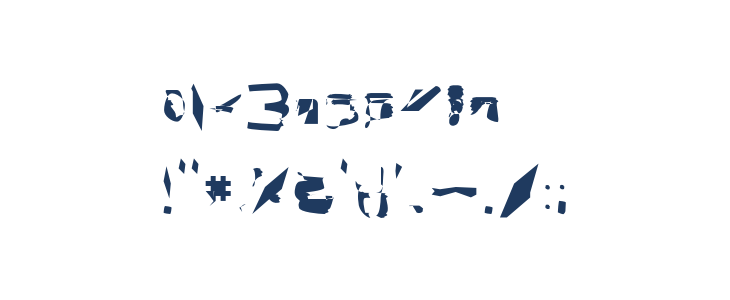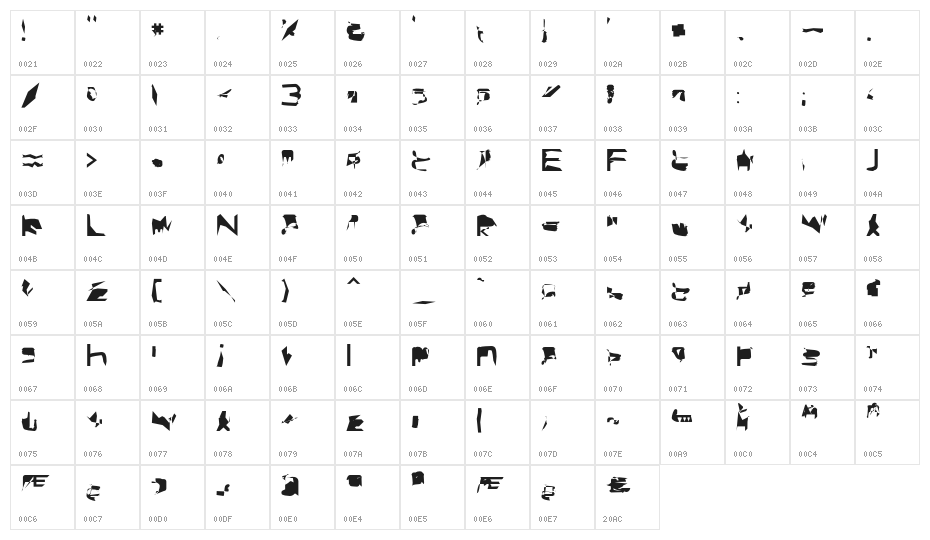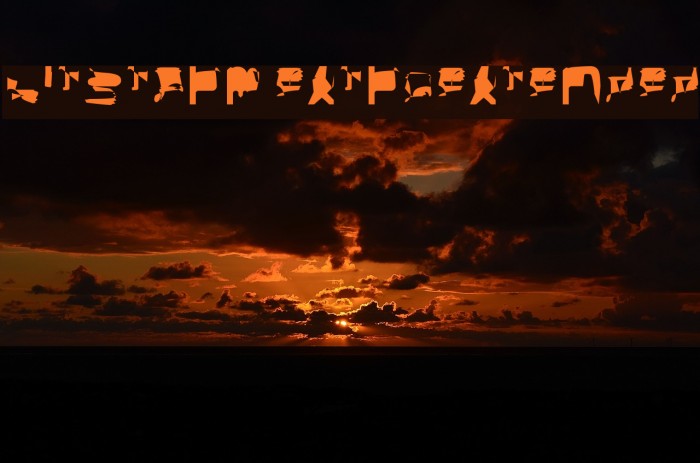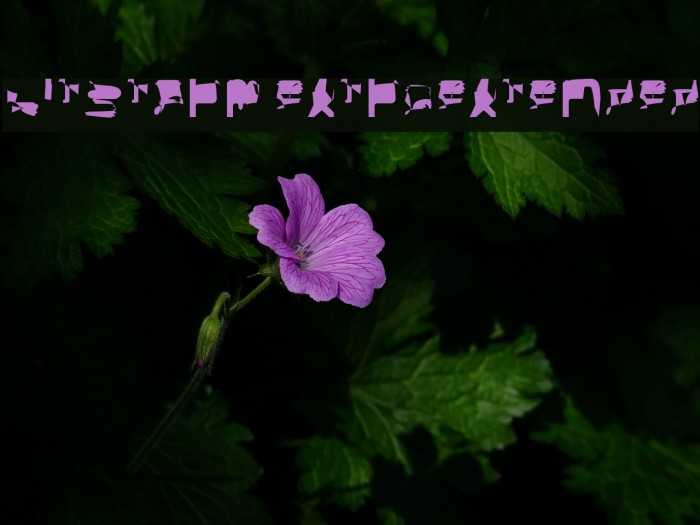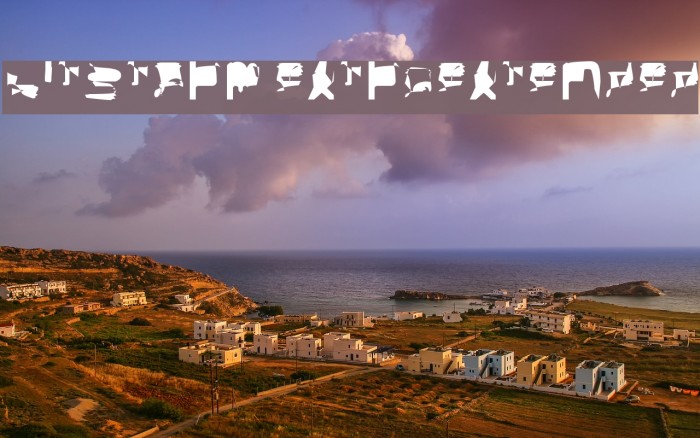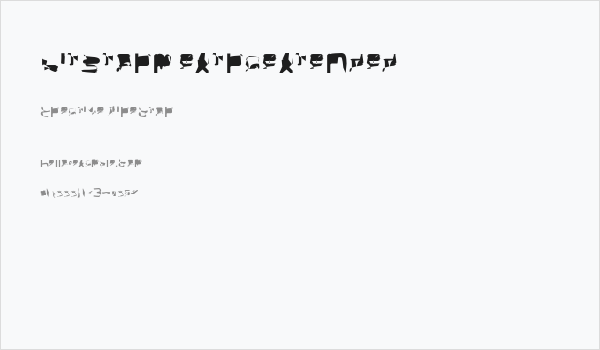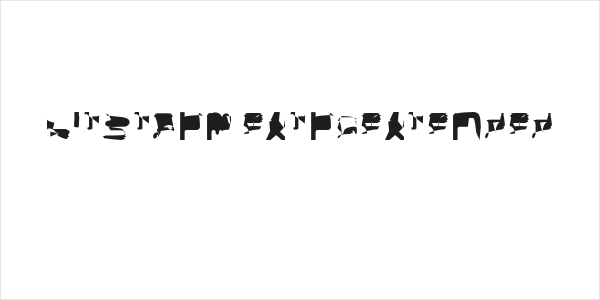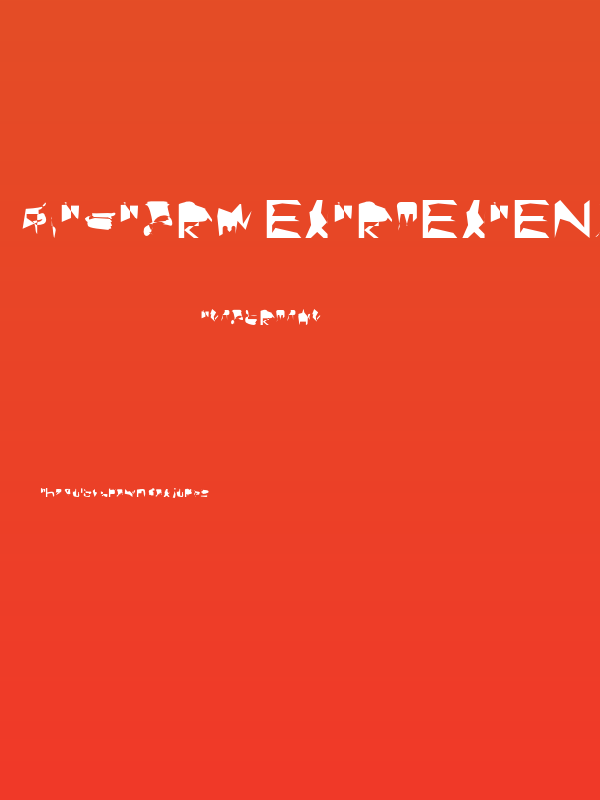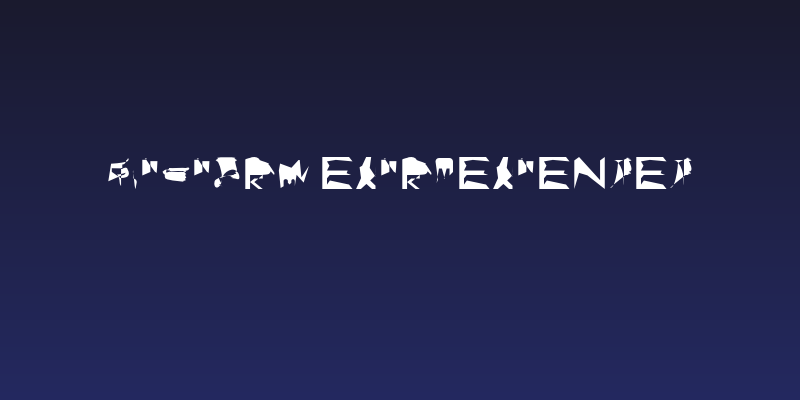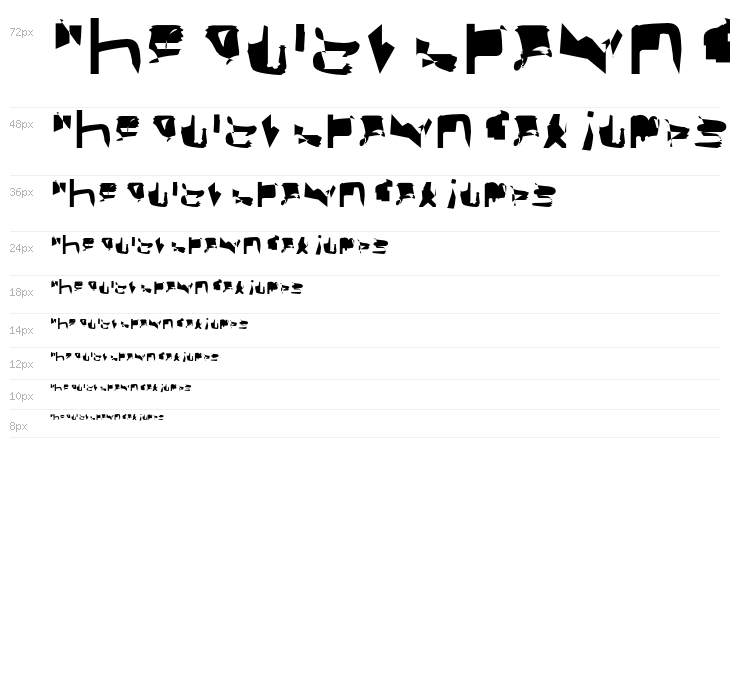
bitstorm extraextended Font
| Nume | bitstorm extraextended |
| Stil general | Modern, Abstract |
| Caz de utilizare | Headlines, Logos, Artistic displays |
| Proiecte propuse | Ideal for album covers, avant-garde posters, experimental art projects, and edgy branding materials. |